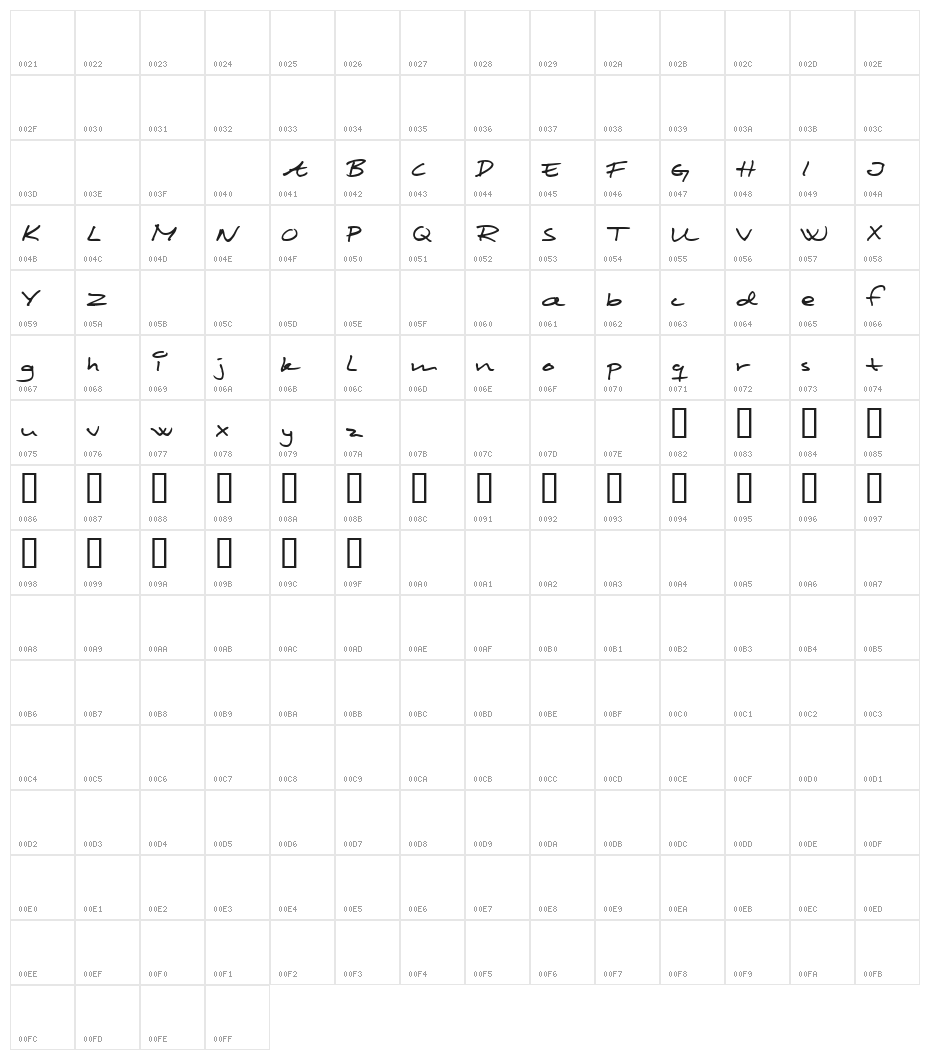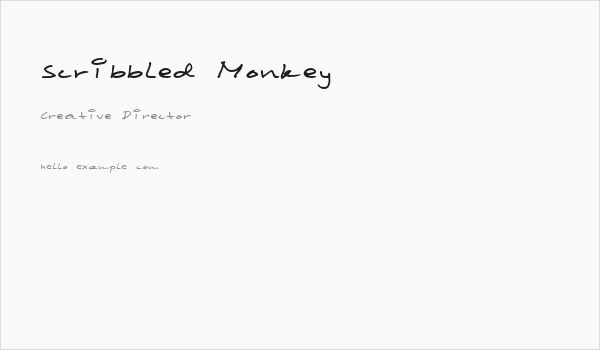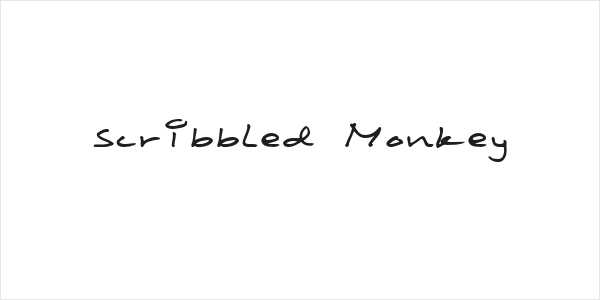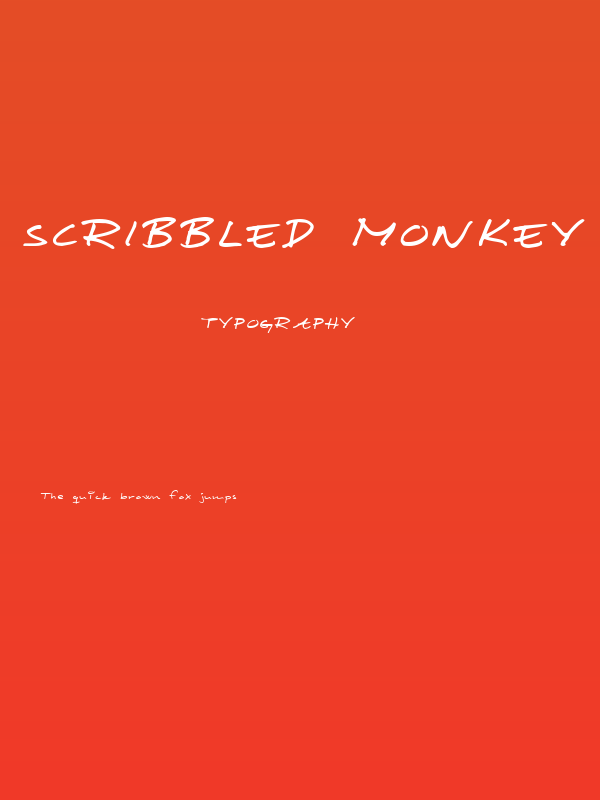
Scribbled Monkey Font
| Style général | Casual |
| Cas d'utilisation | Logos, Headlines, Informal Text |
| Projets proposés | Ideal for greeting cards, personal notes, informal invitations, and creative branding projects. |